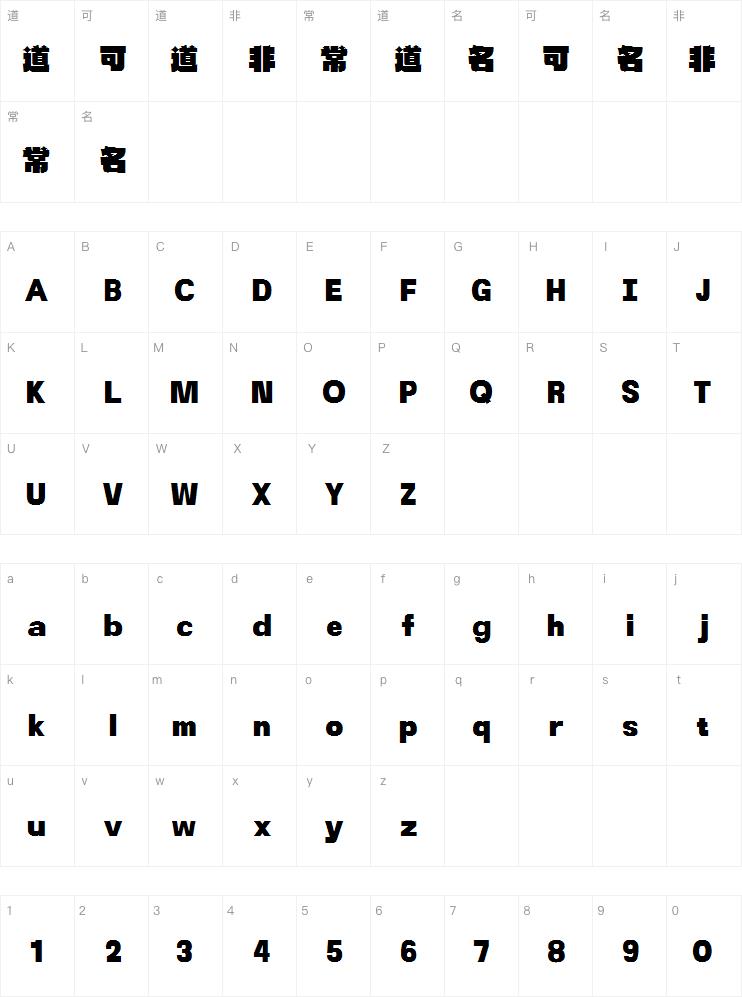
山海创世黑w
山海创世黑,是一款全新的字体,包含汉字9169个,符号200+个。该字体是一款综艺黑体字体,是一款具有强劲视觉冲击力的综艺风格标题字体。字形充实填满整个字框,造型硬朗。直线与圆弧的笔画构成坚实有力,拥有宽大的中宫、粗厚且直线化的笔画设计、简洁明了的笔画切角,带来强有力的视觉冲击效果。该字体在综艺黑体的基础上做了诸多创新,使得该字体既有着流动的美感,又有着端肃的凝重;同时星形点笔画,又使得字体有着冷酷、锐利的元素。在正式用字场合落落大方,在日常使用环境中不失亲切友好,能够在保留综艺黑体基本特征的基础上更能适应当下时尚潮流的需要,助力各大新产品夺取标题主战场。